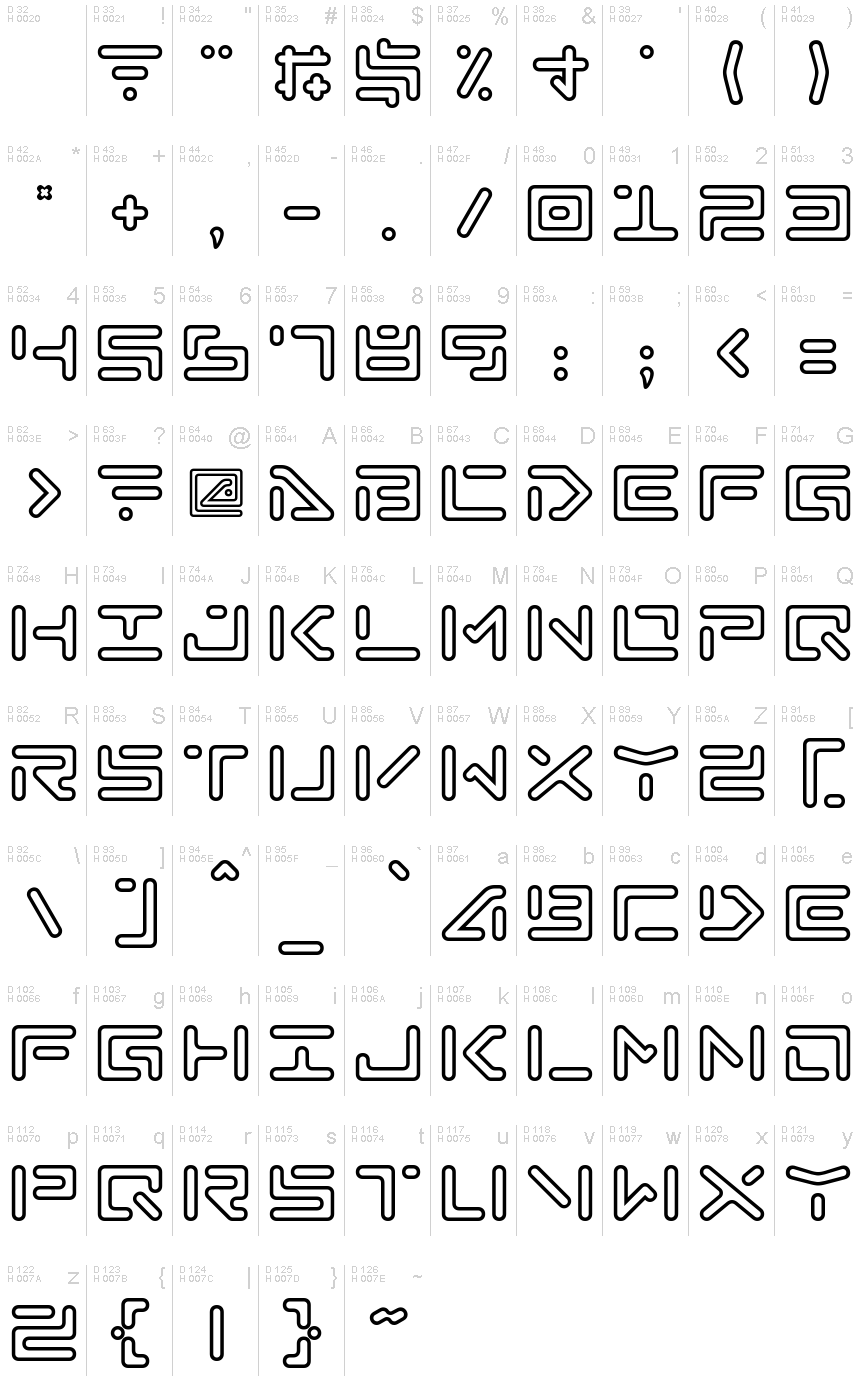
Abduction II, eine fesselnde Display-Schrift aus der Abduction-Familie, entworfen von Rich Gast von GreyWolf WebWorks, strahlt eine kühne, futuristische Ästhetik aus. Diese breite, konturierte Schriftart besticht durch ihren markanten, kantigen Stil, der technische Raffinesse und moderne Avantgarde vermittelt. Dank der scharfen, geometrischen Buchstabenformen und der unverwechselbaren Silhouette ist Abduction II die ideale Wahl für Sci-Fi-Designs, Filmplakate, Spieloberflächen oder jedes Projekt, das eine visuell überzeugende, futuristische Note sucht.
Mit ihrer eleganten Balance zwischen visueller Wirkung und Lesbarkeit ist diese Schriftart äußerst vielseitig und eignet sich hervorragend für verschiedenste Anwendungen, von digitalen Interfaces bis hin zu Printmedien.
Abduction II